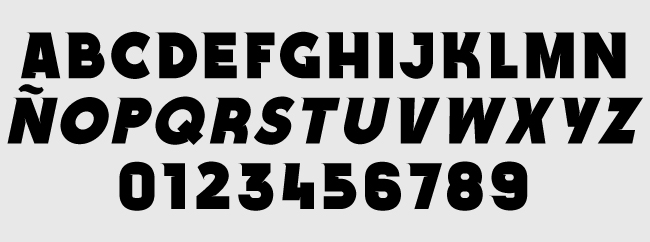
Esta tipografía fue creada en Berlín, tras observar diferentes covers de libros, según nos cuentan sus autores. Sus características se ven a simple vista, como sus curvaturas hacia la izquierda en la parte de arriba de cada letra. Con inspiración en Herb Lubalin, la antiguedad y el Rock. Es una tipografía principalmente bold, pero que funciona fenomenal en titulares.
This typography was created in Berlin, after observing different covers of books, according to their authors. Its characteristics are visible to the naked eye, as its curves to the left at the top of each letter. Inspired by Herb Lubalin, Antiques and Rock. It’s mainly bold typography, but it works great in headlines.